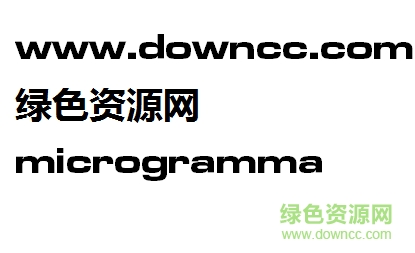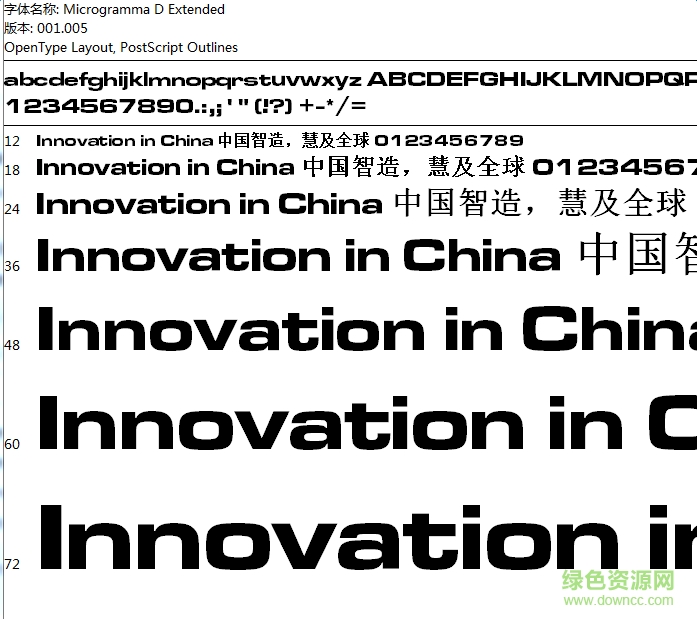
microgramma字體是一款簡(jiǎn)約大方的英文字體,字體端正極具美感,使用流暢時(shí)刻彰顯個(gè)人魅力,適用于多種行業(yè)領(lǐng)域,安裝簡(jiǎn)單即刻使用,綠色資源網(wǎng)誠(chéng)意推薦!還有更多好看的免費(fèi)字體下載等你哦!
microgramma字體是一款應(yīng)用于藝術(shù)設(shè)計(jì)方面的簡(jiǎn)體英文字體,大字效果突出且引人注目,細(xì)節(jié)表現(xiàn)完整,且字庫(kù)完整,可以廣泛應(yīng)用于名片設(shè)計(jì)、新聞媒體、宣傳海報(bào)、ppt、影視制作以及內(nèi)容用字等領(lǐng)域。
該字體非常端正,大方得體,配上古典粗黑,整體十分優(yōu)美好看,在排版字設(shè)計(jì)方面有著不錯(cuò)的應(yīng)用,歡迎下載體驗(yàn)!